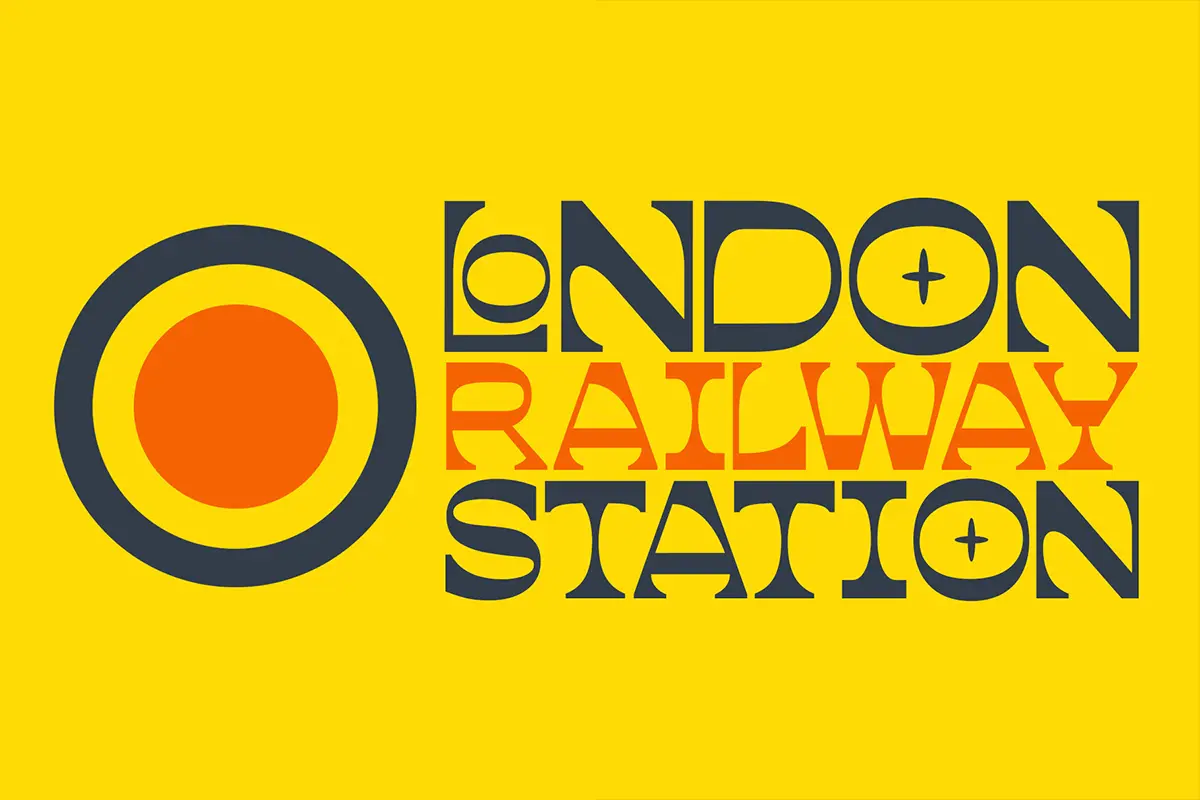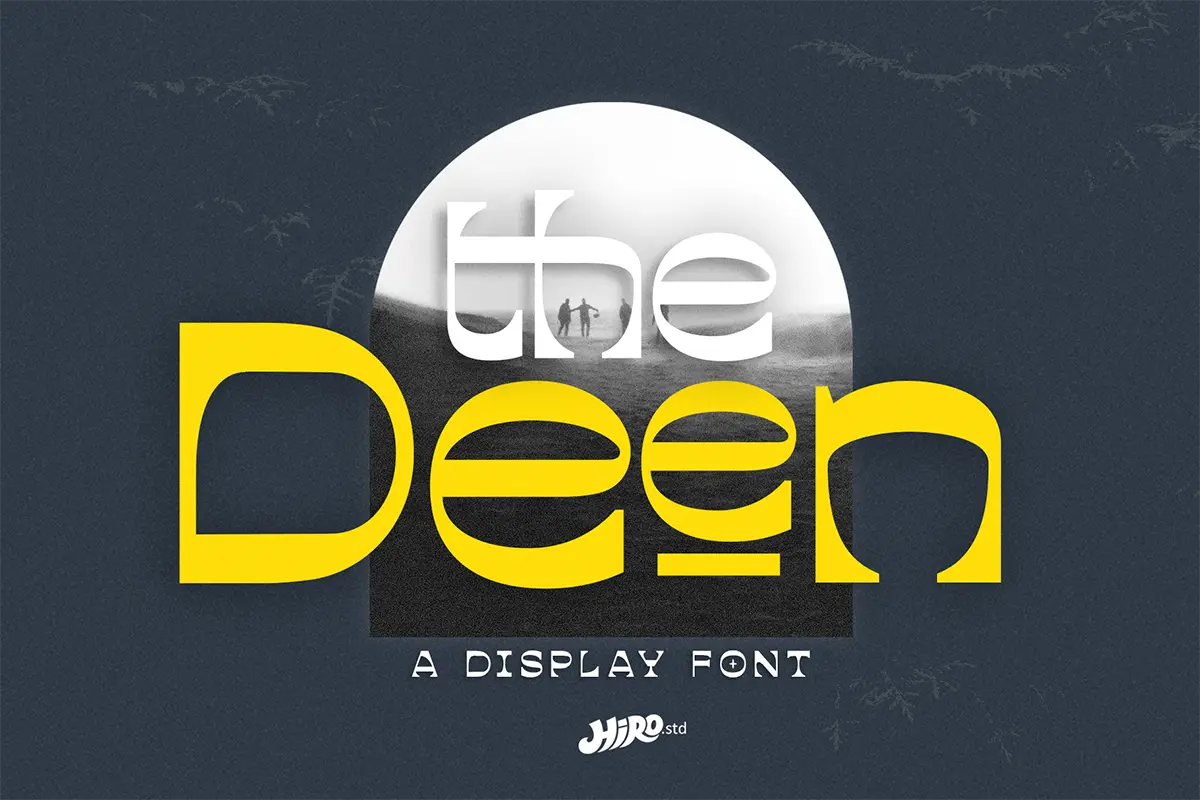
فونت شیک و مدرن
Deen یک فونت اسلبسریف زیبا، مدرن و شیک است که با ترکیب هوشمندانهی استایل شهری (Urban) و حالوهوای رترو وینتیج، تایپوگرافیهایی چشمگیر و متفاوت خلق میکند. این فونت برای پروژههایی که نیاز به یک هویت بصری قوی، خاص و ماندگار دارند، انتخابی فوقالعاده است و میتواند هر طراحی را از حالت معمولی به یک اثر حرفهای تبدیل کند.
فرمهای محکم و در عین حال نرم این فونت باعث میشود در انواع کاربردها—from لوگوتایپ تا پوستر—بهخوبی بدرخشد.
- فونت اسلبسریف مدرن با حس وینتیج
- ترکیب جذاب از استایل شهری و رترو
- مناسب برای:
- لوگوتایپ
- پوستر و تبلیغات
- بستهبندی
- طراحی برند
- تیشرت و محصولات چاپی
- نقلقولهای تایپوگرافی
- شخصیت بصری قوی، متفاوت و چشمگیر
- مناسب برای پروژههای دیجیتال و چاپی